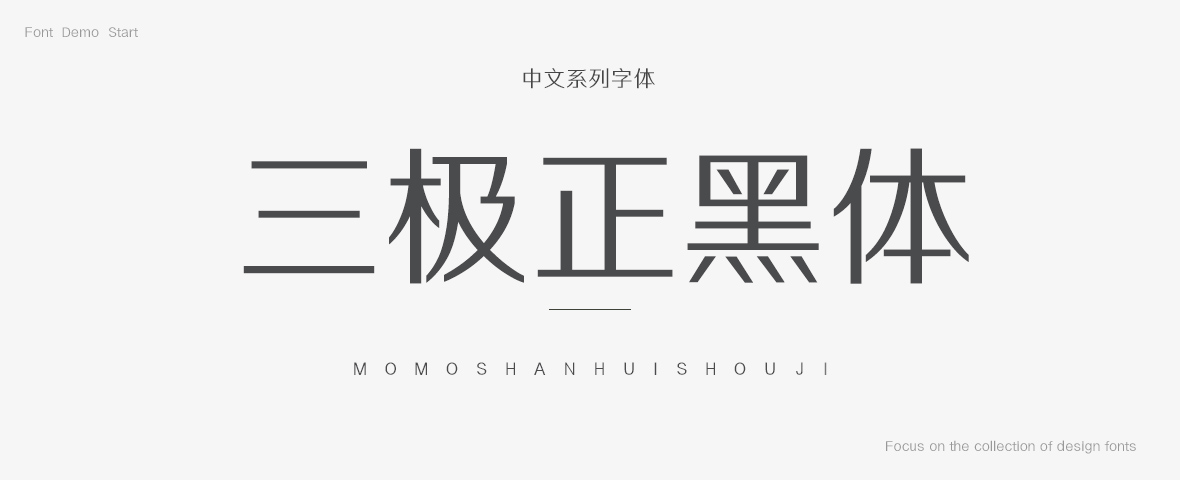
三极正黑体字体
简介:三极正黑体字体是一款家族字体,整个字体系列包含6个字重,字体风格鲜明方正,字体结构干练简洁稳重大气,笔画平直、竖粗横细,撇捺镜像对称稳健。起笔收笔平直,折、钩转折明显,圆润饱满,适用于传统印刷媒介的标题与正文排版、各类屏幕显示及影视字幕等。本款字体由站长素材整理发布,站长字体下载大全提供精选中英文字体素材。